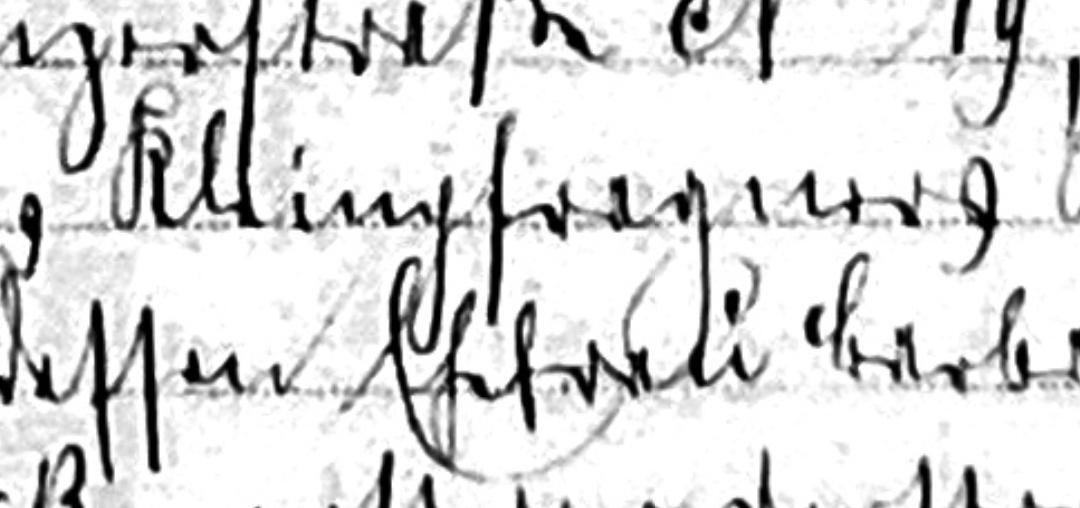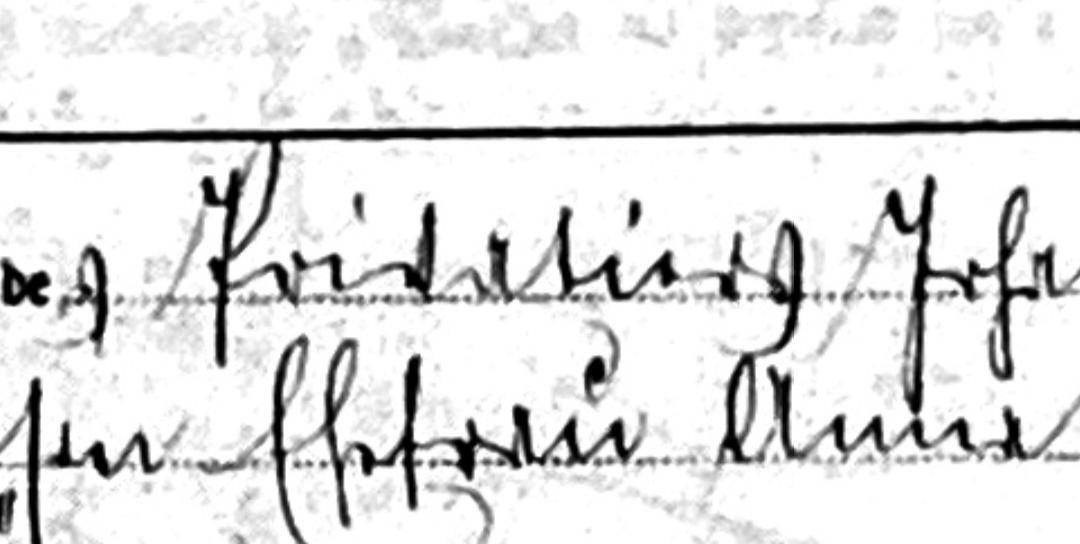
Alte Berufsbezeichnungen entziffern
ich habe mal wieder Urkunden ausfindig machen können und benötige Hilfe bei der Übersetzung von zwei Berufsbezeichnungen. Einzelne Buchstaben kann ich zwar entziffern - die machen aber leider keinen Sinn. Ich danke schon mal für die Unterstützung
Das zweite Wort dürfte Kleinpfragner sein, eine alte Bezeichnung für einen Kleinhändler. Beim ersten Wort ergeben die naheliegenden Lesarten keinen rechten Sinn. Vielleicht lautet der Begriff Privatier, mit gewöhnungsbedürftigem r und v.